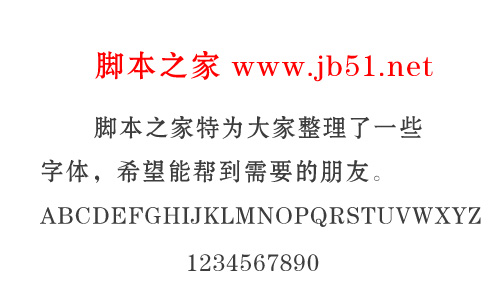
方正宋黑簡體字體是方正字體庫中的一種字體,在宋體字的結(jié)構(gòu)中,融入黑體粗壯穩(wěn)重的特點,故名“宋黑”。宋黑的初始設(shè)計來源于1965年上海印刷技術(shù)研究所徐學(xué)成的鉛字設(shè)計稿,原稿只有4200字,數(shù)字化后進行了擴充。雖源于20世紀(jì)60年代,但字形風(fēng)格卻不受時代影響,仍常用于當(dāng)代各類文化語境。方正宋黑體筆形樸拙、傳統(tǒng),由于橫豎筆畫粗細(xì)接近,具有類似黑體的遠視距效果,在屏幕顯示上的表現(xiàn)也很出色,醒目凝重。喜歡的朋友們可以前來下載使用。